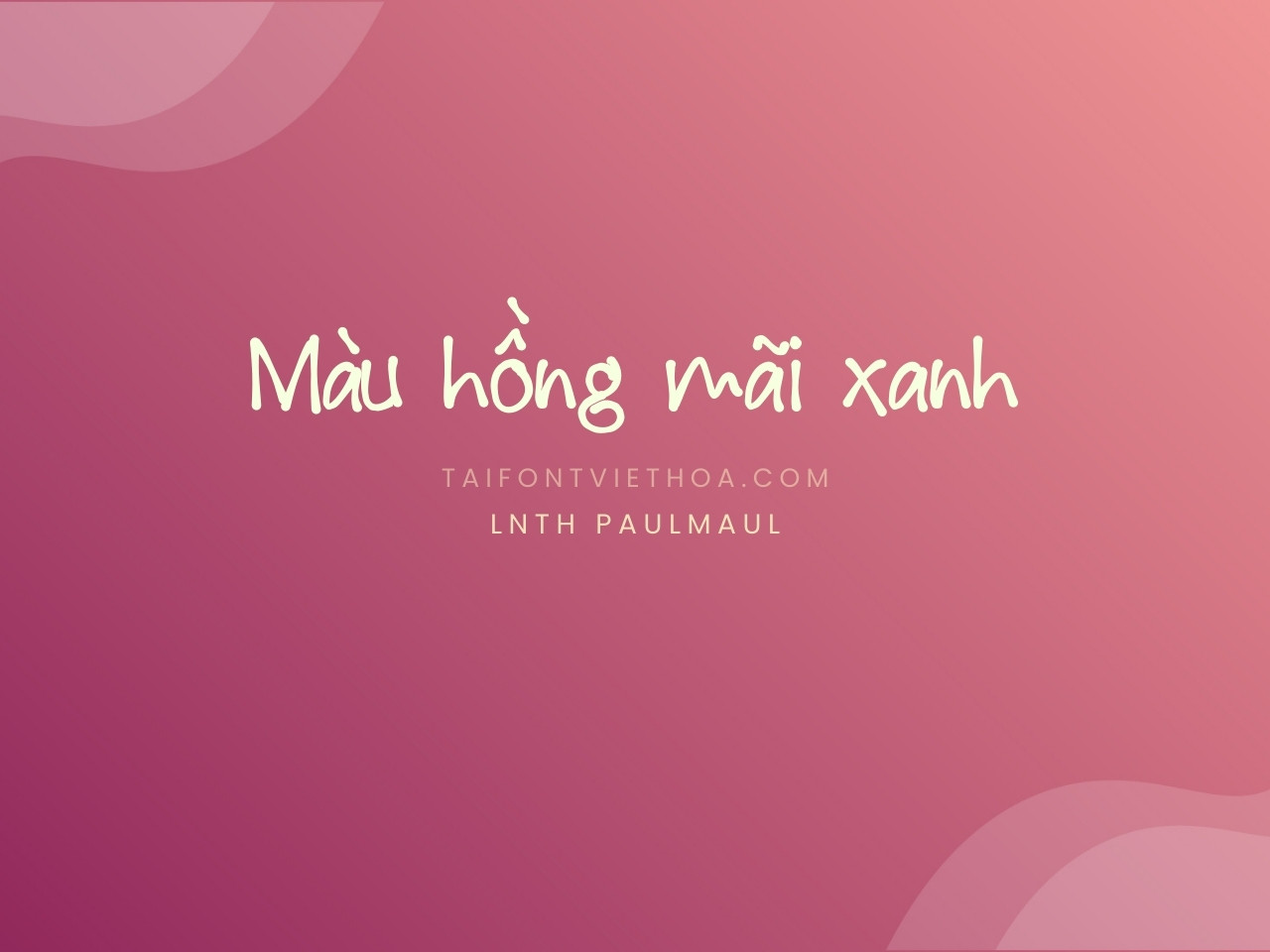
Giới thiệu về font LNTH Paulmaul – Phong cách viết tay hiện đại pha chất retro
LNTH Paulmaul là phiên bản Việt hóa từ font gốc “PaulMaul” được thiết kế bởi Exclamachine Type Foundry – một studio nổi bật với các font mang hơi thở hoài cổ và cá tính riêng biệt. Font Paulmaul mang phong cách viết tay hiện đại, với các nét phóng khoáng, tròn trịa và mềm mại nhưng vẫn giữ được tinh thần retro từ những bảng hiệu, poster xưa. Tuỳn Pucca đã thực hiện Việt hóa trọn bộ, hỗ trợ đầy đủ tiếng Việt và hơn 60 ngôn ngữ khác – giúp font có khả năng ứng dụng toàn cầu.
Font được taifontviethoa.com sưu tầm và chọn lọc để phục vụ nhu cầu sáng tạo cá nhân hóa, thiết kế sự kiện, poster retro hoặc các ứng dụng gợi nhắc đến thời kỳ hoàng kim của quảng cáo truyền thống. Đây là một lựa chọn đáng giá cho những ai đang tìm kiếm một kiểu chữ mềm mại, cá tính và đậm chất vintage hiện đại.
Đặc điểm thiết kế và ứng dụng nổi bật của LNTH Paulmaul
LNTH Paulmaul mang dáng dấp của chữ viết tay tự nhiên, có độ nghiêng nhẹ, với các nét bo tròn và khoảng cách thoáng. Font có độ tương phản trung bình, rất dễ đọc và tạo cảm giác gần gũi, thân thiện. Những đường nét mềm mại giúp nó phù hợp cho các thiết kế cá nhân, sự kiện hoặc các thương hiệu nhấn mạnh yếu tố cảm xúc và sự kết nối.
LNTH Paulmaul thích hợp với các ngành như bất động sản, công nghệ, mỹ phẩm, giáo dục, đồ thủ công, và dịch vụ cá nhân hóa. Các ứng dụng nổi bật gồm: thiệp sinh nhật, tiêu đề poster lễ hội, bộ nhận diện thương hiệu handmade, ảnh mạng xã hội, sản phẩm sáng tạo hoặc các chiến dịch branding dành cho khách hàng trẻ trung, năng động.